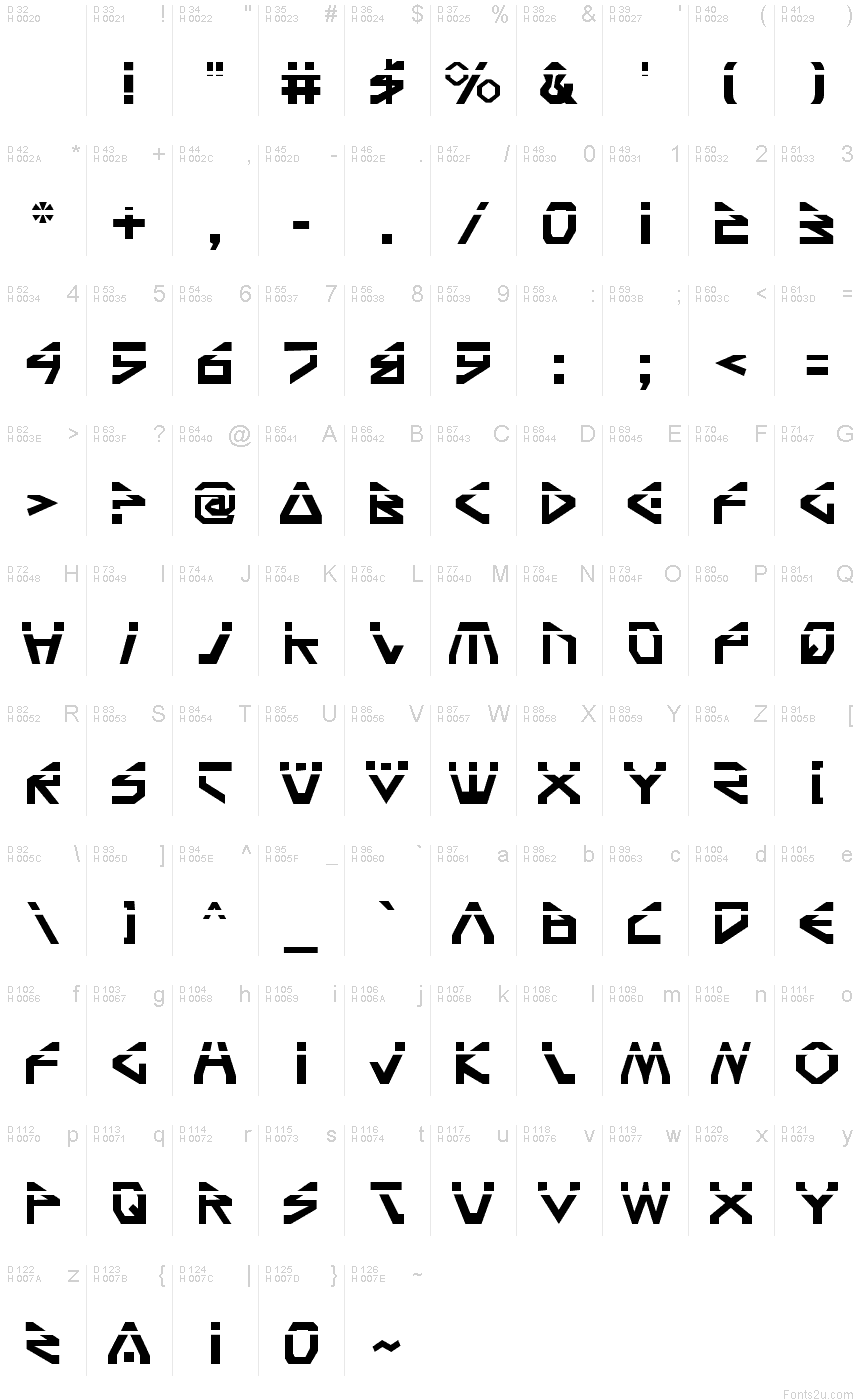
Terra Firma Laser von Iconian Fonts ist eine kostenlose Techno-Display-Schriftart mit dem kantigen, metallischen Look von Retro-Sci-Fi-Marken. Die Buchstaben bestechen durch steile Diagonalen, quadratische Ecken und scharfe Schnitte, die die Großbuchstaben wirken lassen, als wären sie konstruiert statt gezeichnet. Der wuchtige Rhythmus erinnert direkt an Arcade-Automaten und frühe Computer-Actionspiele.
Diese Gratis-Schrift eignet sich perfekt für Plakate, Spiele-Logos, Album-Cover, Titelkarten und kurze Verpackungs-Headlines, bei denen Sie diesen strengen, futuristischen Ton suchen, ohne in ein glattes Minimalismus-Design abzudriften. Auch für Monogramme und kurze Zeilen ist sie ideal, da die angewinkelten Schnitte und breiten Formen selbst wenigen Buchstaben eine kraftvolle, maschinelle Präsenz verleihen.